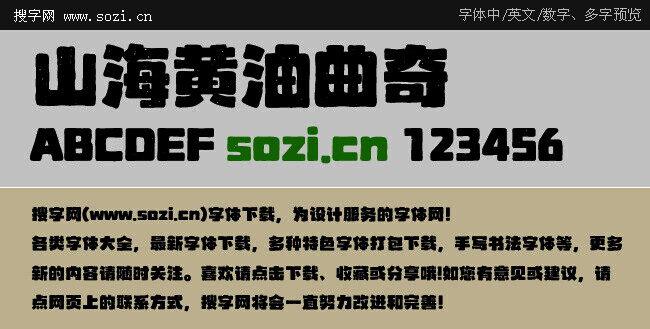
山海黃油曲奇
搜字網(wǎng)提供一款山海黃油曲奇中文藝術(shù)字體下載,該字體是一款具有強(qiáng)勁視覺(jué)沖擊力的粗體字體。字形粗大,充實(shí)填滿(mǎn)整個(gè)字框。風(fēng)格童趣,結(jié)構(gòu)多變靈動(dòng),線條柔和。字形中融入手繪風(fēng)元素及手繪鏤空元素,宛如一個(gè)個(gè)黃油曲奇餅干,造型生動(dòng)有趣,具有靈活的適用性,天真俏皮又不失時(shí)尚感。適合包裝設(shè)計(jì)、海報(bào)設(shè)計(jì)、廣告設(shè)計(jì)等應(yīng)用。